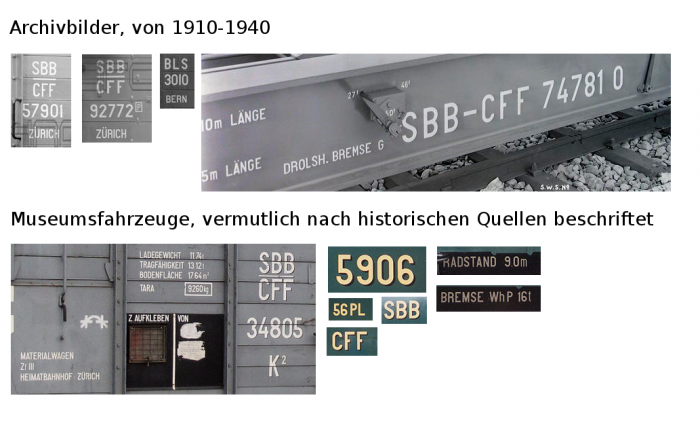
Beschriftungen von Schweizer Eisenbahnfahrzeugen, ca. 1900-1950
Ich suche eine Schrift, die jener ähnelt, die im frühen 20. Jahrhundert in der Schweiz zur Beschriftung von Eisenbahnfahrzeugen, besonders Güterwagen, verwendet wurde.
Es scheint Unterschiede zwischen den SBB und Privatbahnen wie der BLS zu geben (Vergleiche "1" im obigen Bild), aber allgemein haben die damals verwendeten Schriften einen recht typischen, gemeinsamen "Charakter".
Es gibt Gemeinsamkeiten mit DIN 1451, welche ähnliche Anwendungsbereiche hatte, aber auch einige markante Unterschiede, z.B. bei E oder 7.
Vom "Gefühl" her stimmt Cervo Regular von Typeforge Studio recht gut, aber auch hier stimmen E, M oder 4 nicht.
Was könnte besser passen?
Hat vielleicht sogar jemand weitere Informationen zu den verwendeten Schriften und deren Geschichte?
Mit Verlaub, die Don weist sicherlich gewisse Ähnlichkeiten mit den Eisenbahnschriften auf, wie auch die DIN-Schriften.
Selbstredend darf man keine 1:1-Entsprechung erwarten, denn eine Industriebeschriftungsschablonenproduktion von 1920 oder 1950 hat mit einer Fontproduktion von 2000 oder 2015  erstmal gar nichts zu tun.